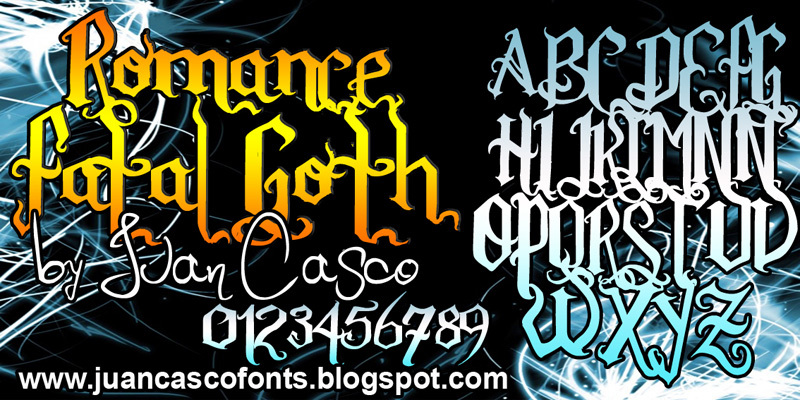
Romance Fatal Goth Premium di Juan Casco è un carattere gotico medievale gratuito dall'impronta teatrale. I suoi tratti angolari, le giunzioni appuntite e le ampie volute conferiscono alle lettere una silhouette decorata e disegnata a mano, con un tono romantico e leggermente ribelle.
I marchi di moda alternativa e di musica dark possono utilizzare le sue forme drammatiche per loghi, packaging e merchandising a tiratura limitata. Nell'editoria, il suo elaborato tratto calligrafico è particolarmente adatto per copertine di libri fantasy e articoli di riviste storiche riccamente illustrati.
Gothic version of Romance Fatal